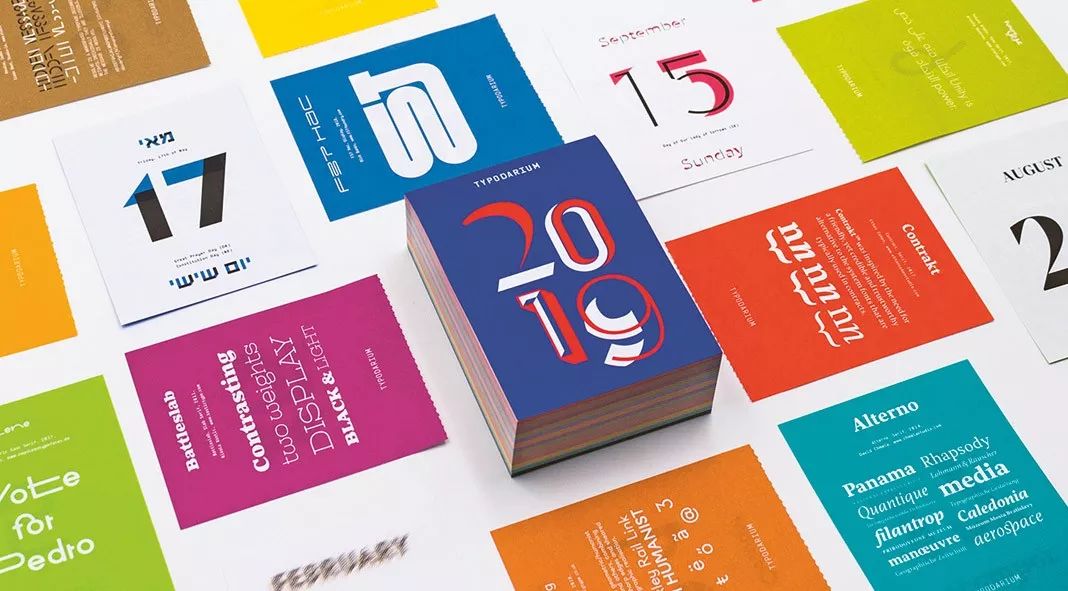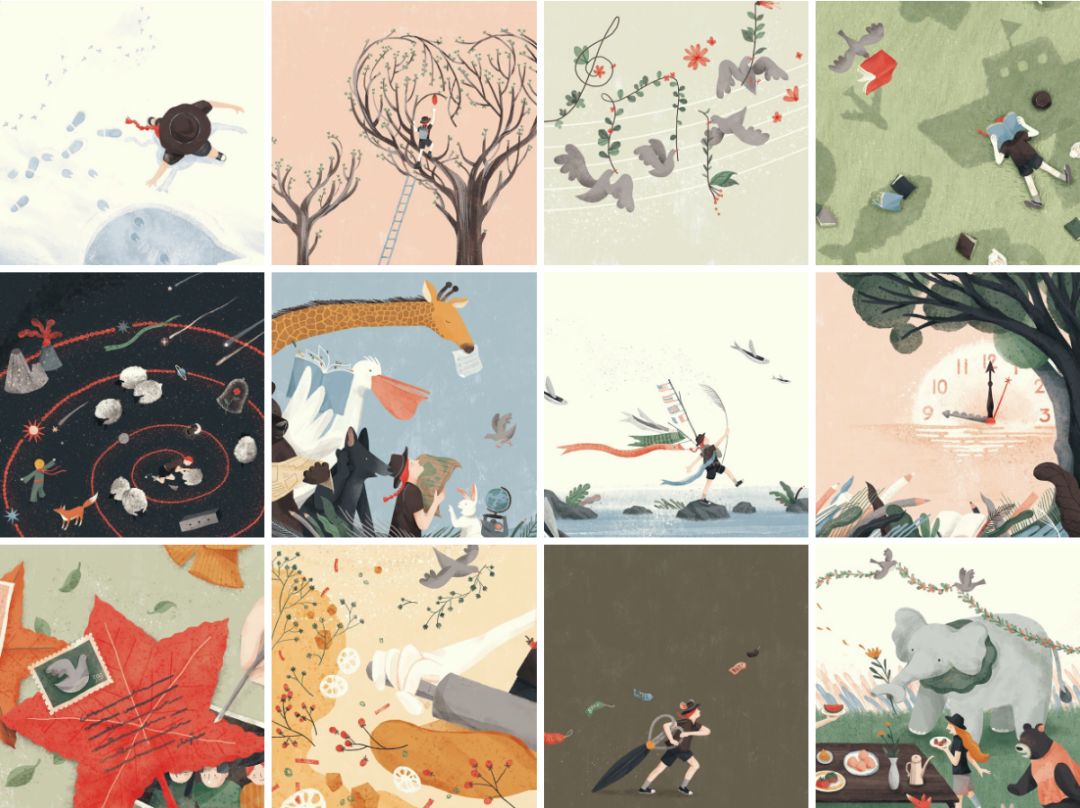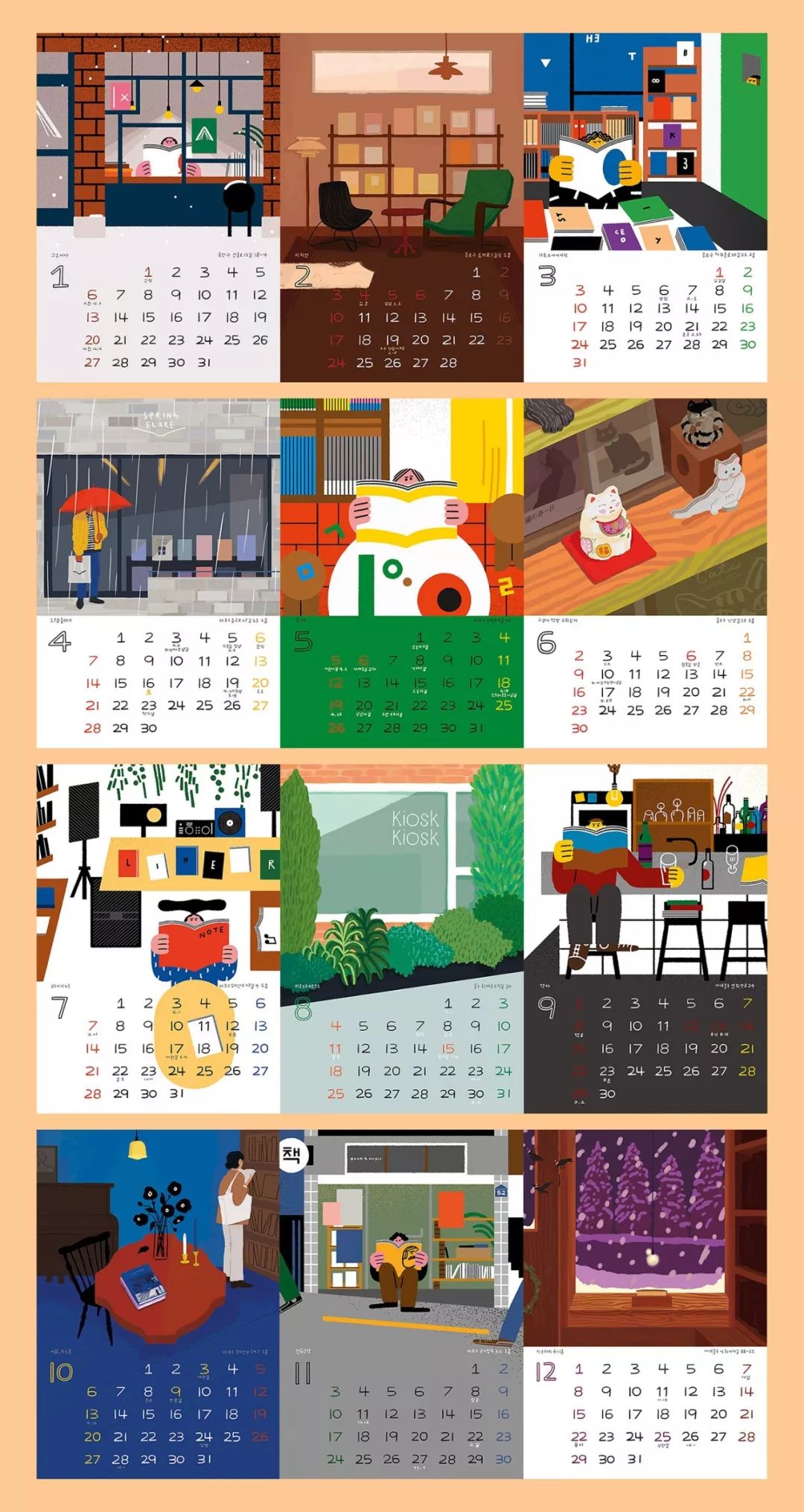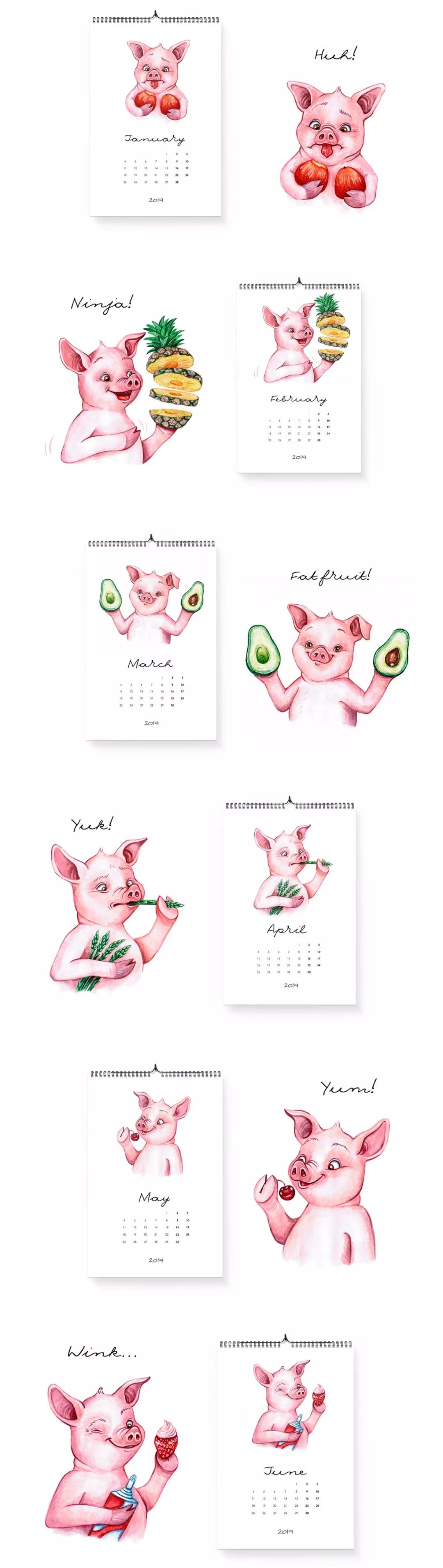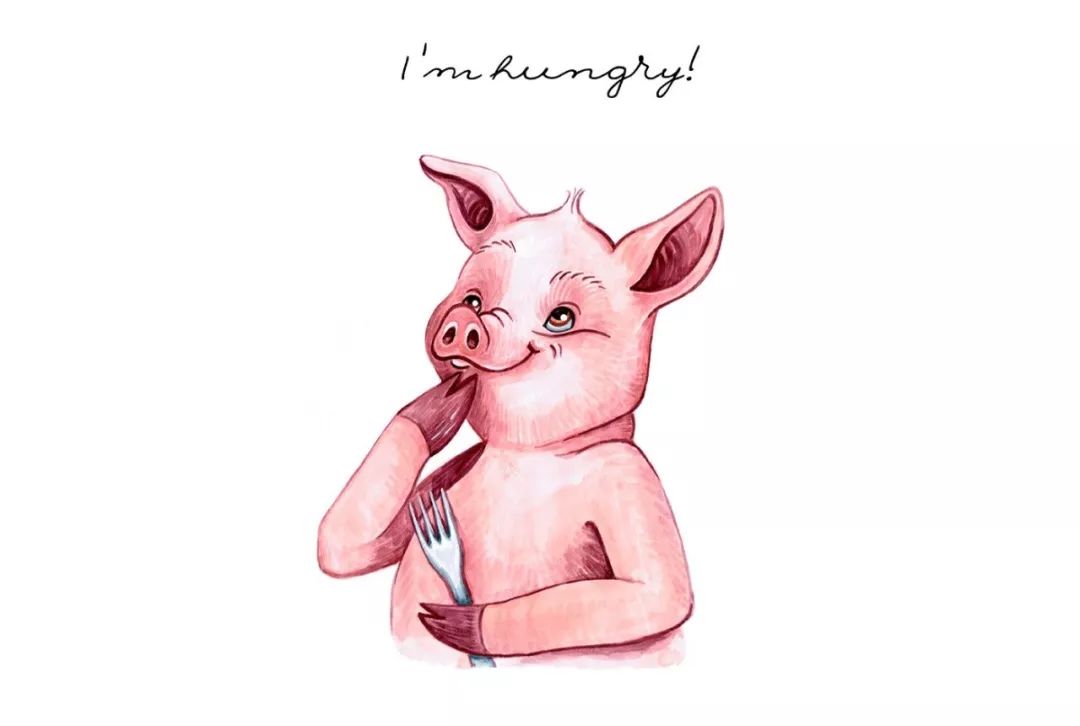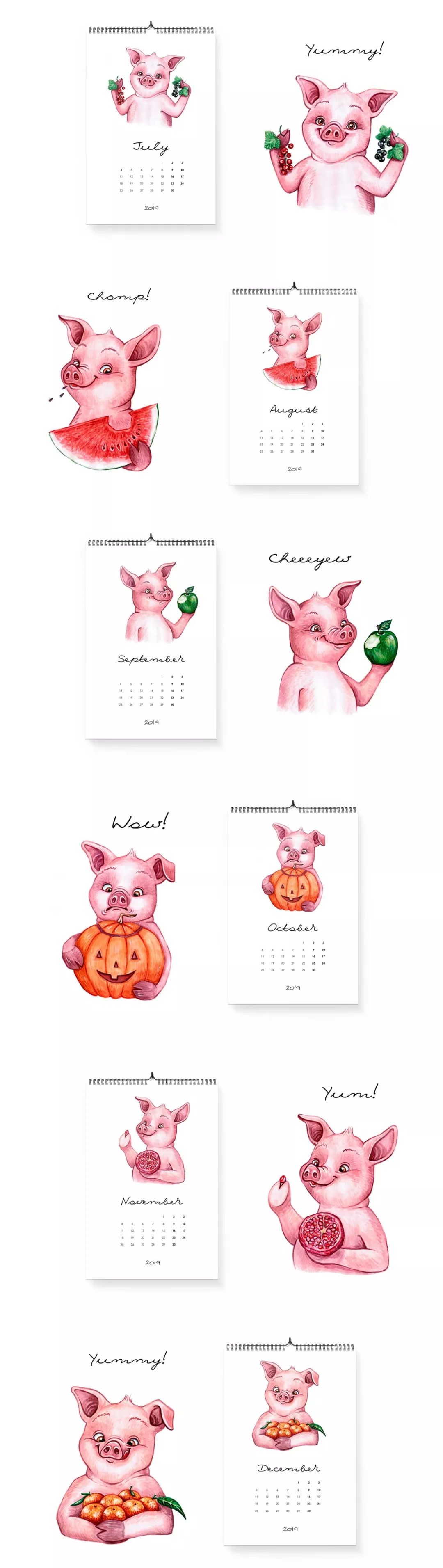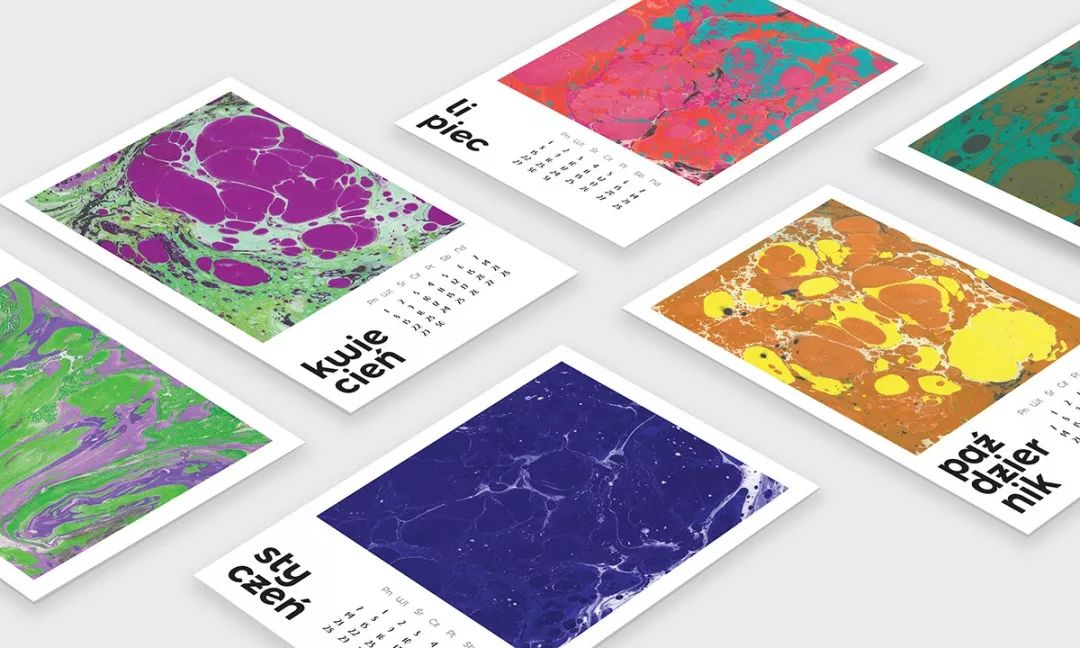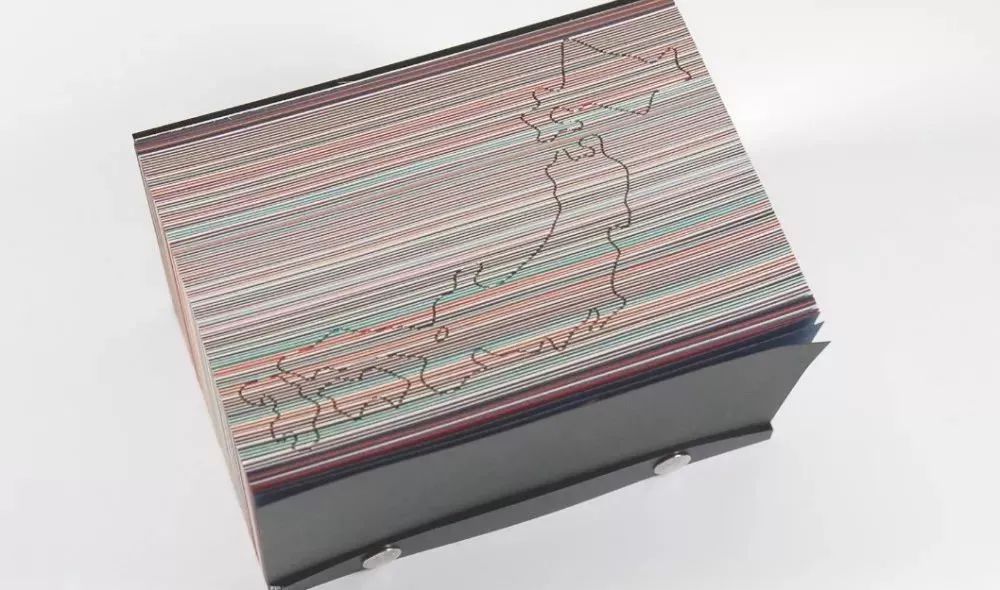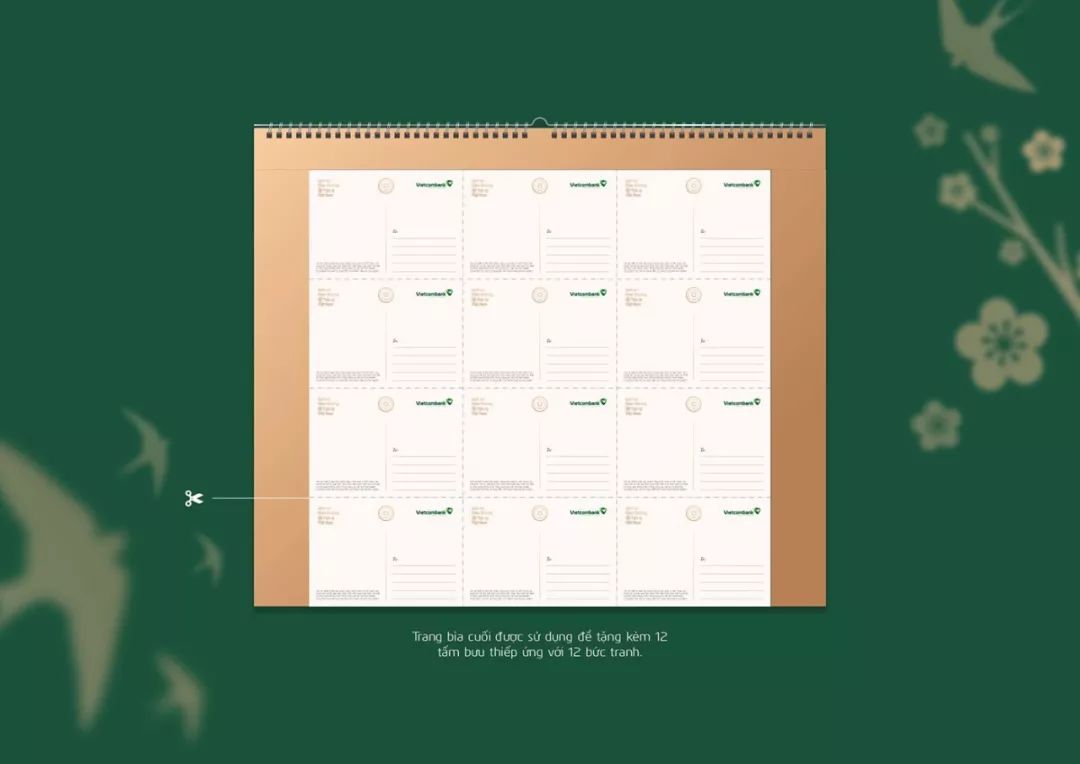
看到Behance上这些耐撕的日历设计,感觉2019都不焦虑了
昨天柚子刷微博时,看到一个话题,叫“2018只剩下一个月了……”
按往常来说,我可能会感慨时光,但今年发生了太多悲伤的事情,我只想拉动快进条,马上进入2019。
特别是在behance上,看到这些颜值超高的日历,我就更想坐时光机了,感觉每撕一页,都能和一个艺术家不期而遇~
这些字体好清奇
每年Typodarium都会出本创意日历,365天每天一个字体,可以说是资源库了。2019走的是色彩缤纷的感觉,你可以发现最新的字体和排版,平面设计师应该会对它欲罢不能。
这款Mr Cup2019日历很像《神奇动物2》里的魔法书,每个月都为创意人提供一句励志名言,由多名排印师和平面设计师共同设计而成,采用了复古风格和漂亮的浮雕,既可以当日历,也可以做灵感手抄本。
但凡是图片和字体结合的,都很有代入感,比如这款,还有3D既视感。
看着像泰国的画风,但文字又偏德国,比如oktober、desember是什么鬼?
这些插画好温暖
来自台湾的 Nani Book,整本都在讲“理想的生活”这个故事。你总能从中找到生活、工作的道具,特别是2019那四个数字,很像探险家。
这是一个韩国设计师的作品,但总感觉是我们日常的自画像,但有一点不同的是,他总拿着书,我们总拿着手机,哈哈!
虽然现在人已经很少买挂历了,但如果是这种艺术画,还是有点吸引力的。
发现了吗?这款日历把字体和插画结合得很好,可以借鉴哦。
最喜欢这个小猪了,感觉从一月份到十二月份都是在吃各种水果,人不如猪啊!
这些脑洞好艺术
有一些日历还能提高你的艺商,特别是没想法,一团浆糊的时候,它总能给你灵感。
这个日历叫什么,设计师请大声说,肌理~
将星座和十二月份结合起来,是不是可以兼职算塔罗牌了?
每个人都曾是小黑、小白,总有孤独、狼狈的时候,他画到你心里去了吗?
这些日历好炫酷
传家日历一直很火爆,被誉为生活指南,2019特别加入了AR,以重逢为主题,真的是要掏你的心(钱)窝(包)了。
这是一个给越南银行设计的日历,很有中国风,色彩运用的也很好,要银行都是这种日历,应该就不怕送不出去了。
日本纸雕公司TRIAD又联合Tokyu Hands,出了2019年的纸雕日历,名叫OMOSHIROI CALENDAR,共有365页。
每撕下一页,都会有微妙的变化,随着日子流逝,你会发现东京塔?浅草雷门?简直就是买不起的艺术品(3000软妹币)。
Telegramme处处闻啼鸟日历,最一目了然。把一年更直观地分割成几个周、几个月和几个季节。而四季中的准确报时,分别交给了春天的大山雀,夏天的金翅雀,秋天的黑鸟,冬天的知更鸟。
离2019还有一个月零3天~